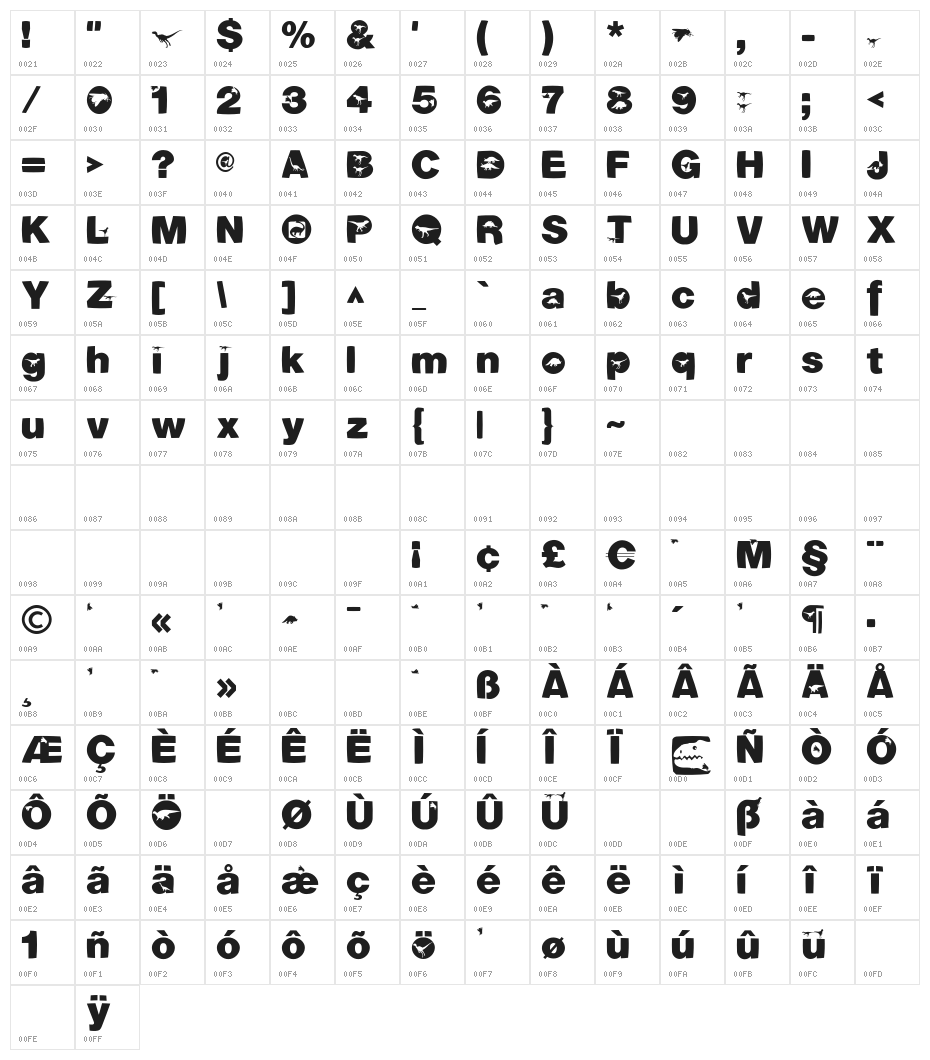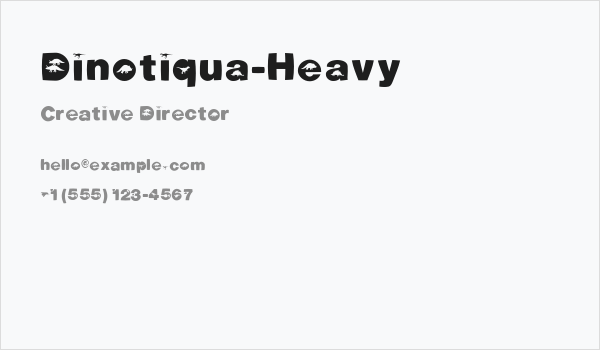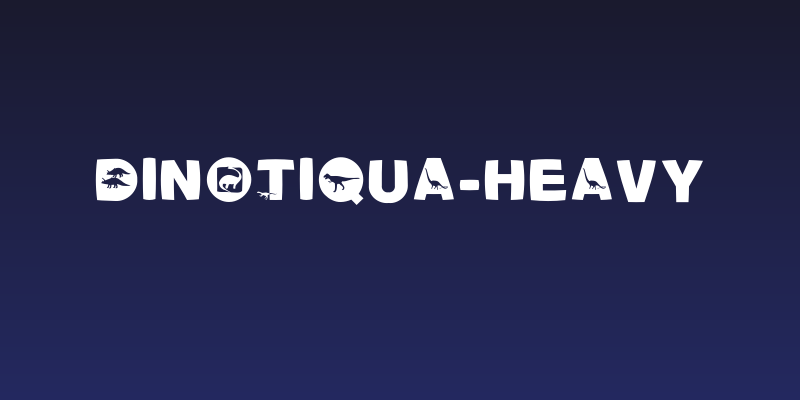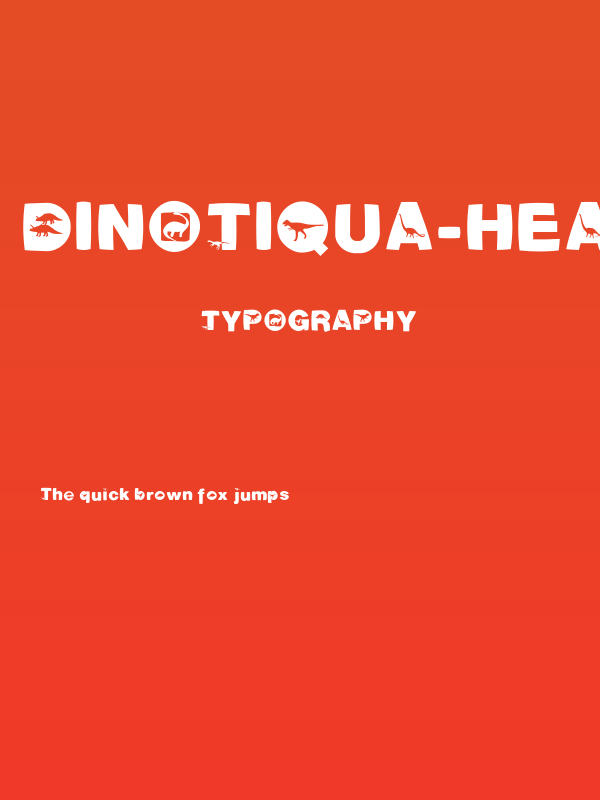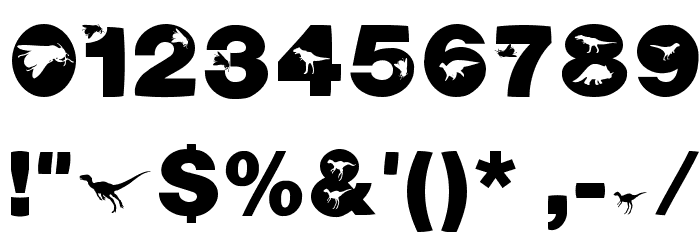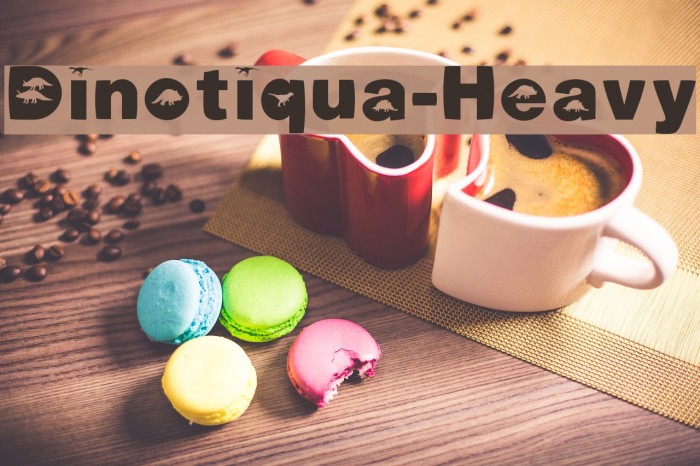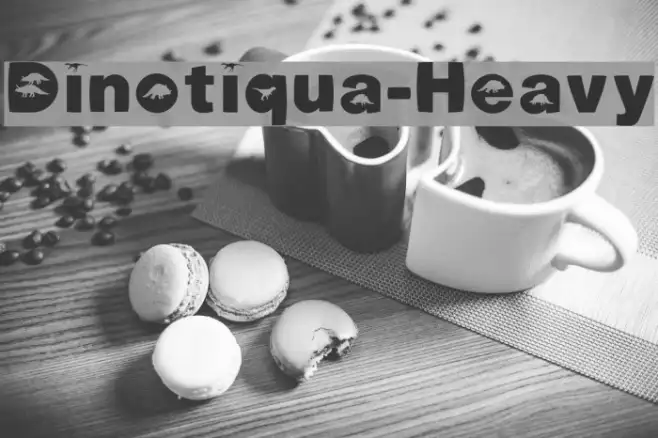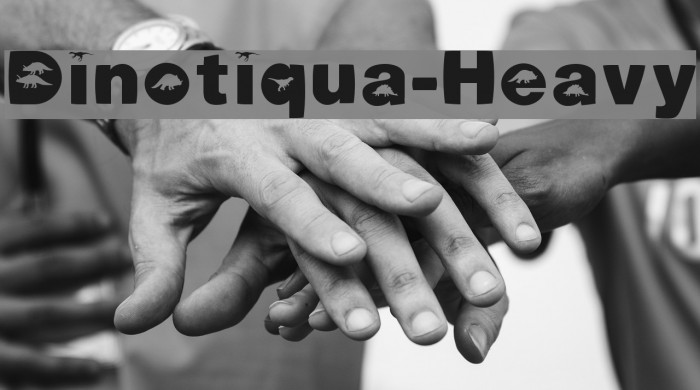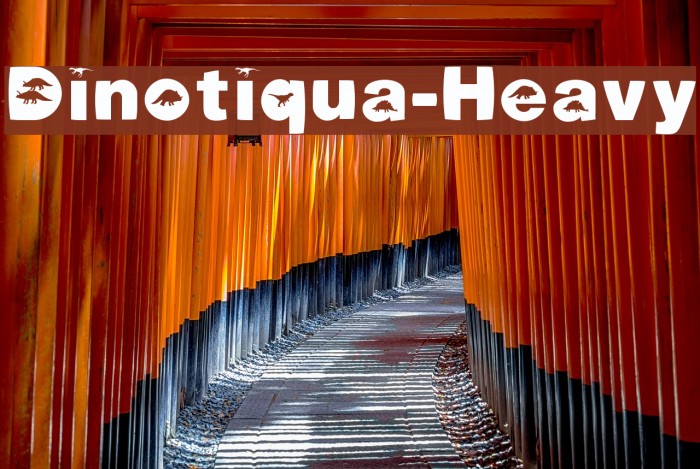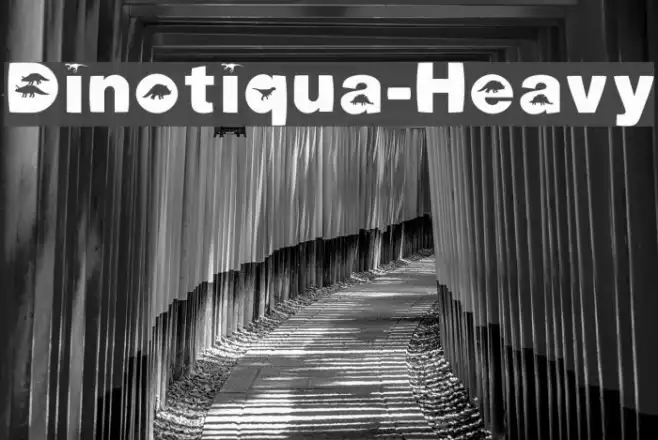
Dinotiqua-Heavy Font
| Stile generale | Playful, Thematic |
| Progetti proposti | Ideal for children's books, educational materials, themed party invitations, and playful branding projects. |